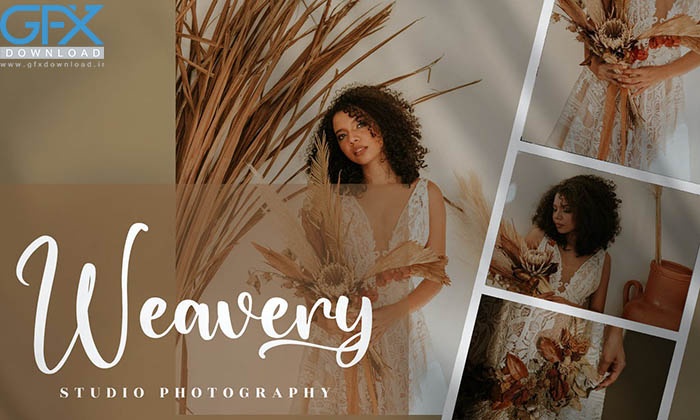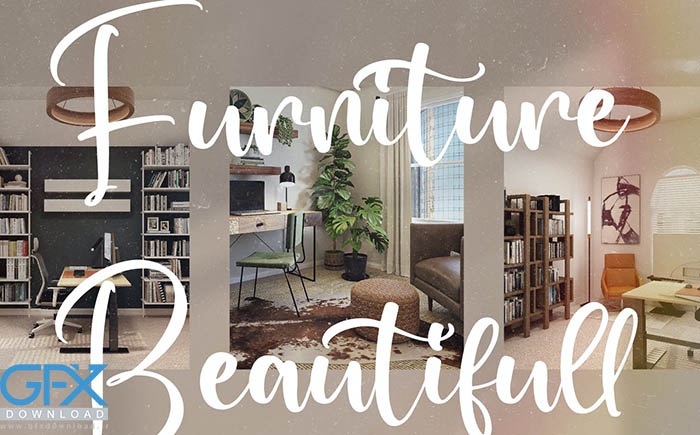
این فونت زیبا یکی از فونت های کاربردی است که برای تکمیل محصولات خلاقانه دیجیتال و چاپی شما مناسب است. دانلود فونت مدرن Bucket Honey برای پوسترها، پست های رسانه های اجتماعی، برندسازی، پروژه های شخصی و غیره عالی است. شامل فایل های OTF - WOFF - TTF می باشد.